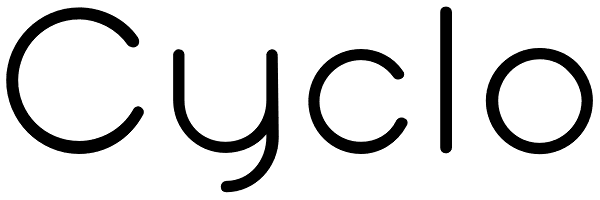
Cyclo
Ainsi que le considérait Geoffroy Tory, typographe et philosophe de la Renaissance, chaque lettre de l'alphabet peut être dessinée à partir d'un cercle et d'un trait. La fonte "cyclo" actualise et radicalise ce principe graphique visionnaire. Le...